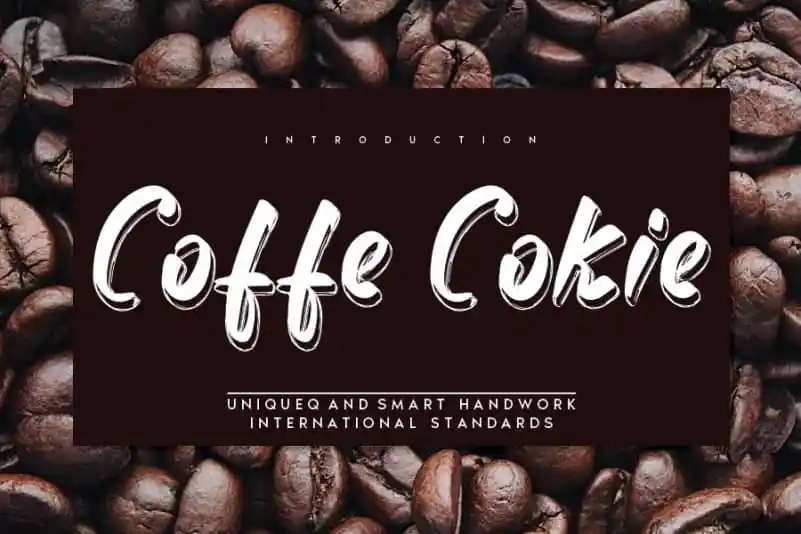
Coffe Cokie Script Font – Fonte Grátis
Coffe Cokie Script Font
A Coffe Cokie Script Font é uma elegante escolha para qualquer projeto criativo. Criada usando uma pena a esferográfica, essa fórmula única apresenta uma escrita livre à mão clara e um pouco quixotesca, adequando-se perfeitamente a logos, branding, projetos do Instagram e até DIY de artesanato. Sua forma limpa permite que você personalize seus materiais de comunicação com personalidade e frescura, ideal para quem procura algo não convencional no universo das fórmulas de escrita. Esta fonte tem um toque agradável à mão que certamente dará aos teus projetos um toque autêntico e único. Ideal para aquelas pessoas que buscam uma identidade visual distintiva.